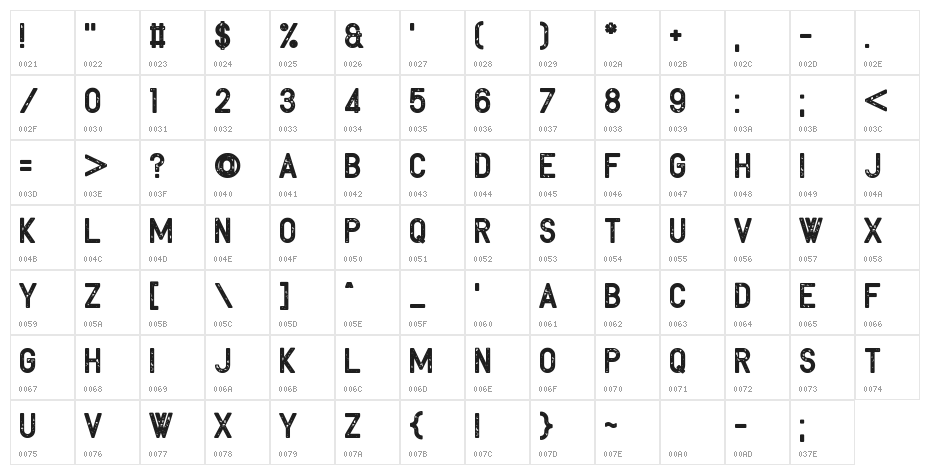
Toreadore Font
✎ Messy
| 分类 | Messy |
| 整体风格 | Vintage |
| 推荐项目 | Ideal for posters, branding, album covers, and any design requiring a bold, vintage aesthetic. |